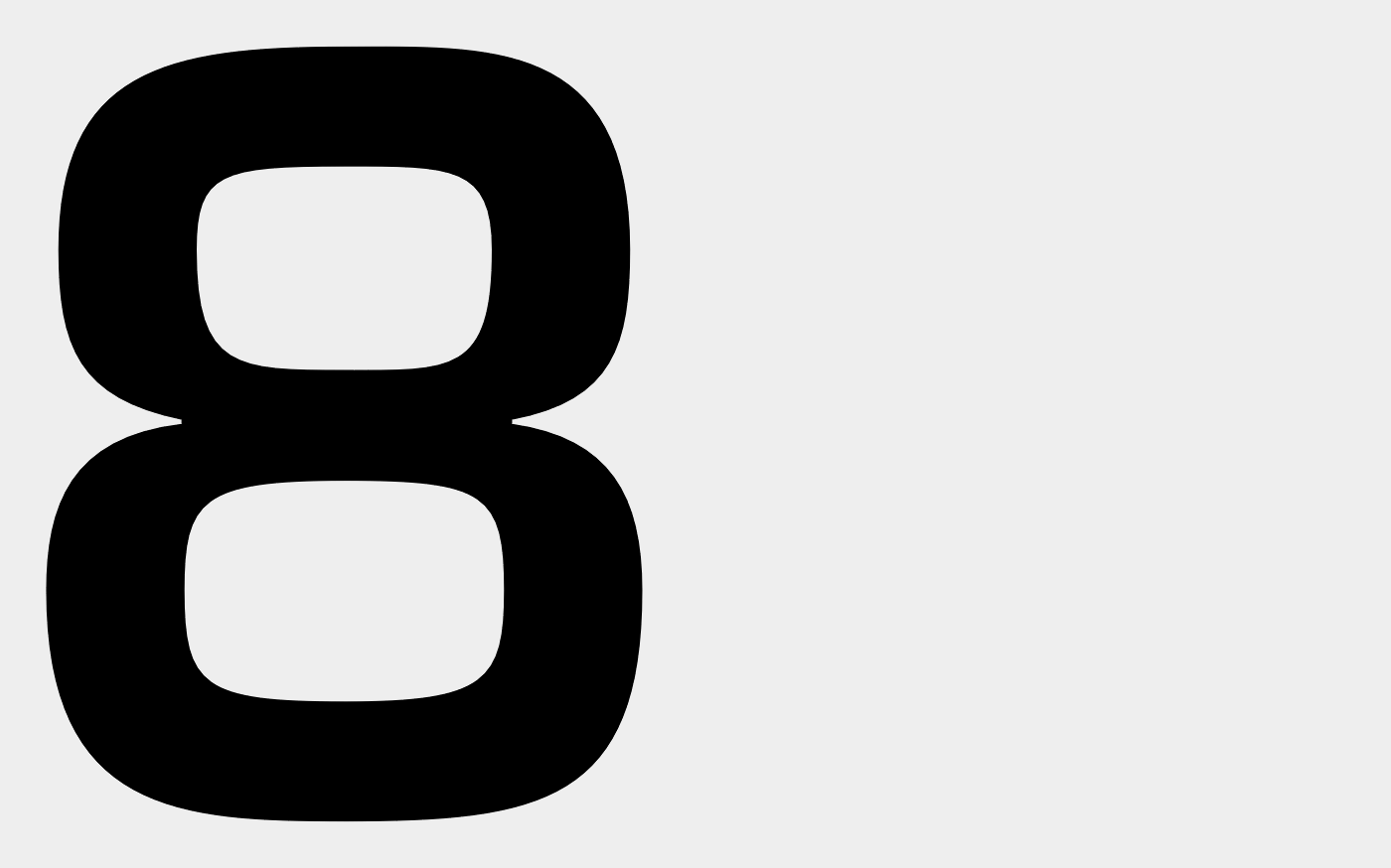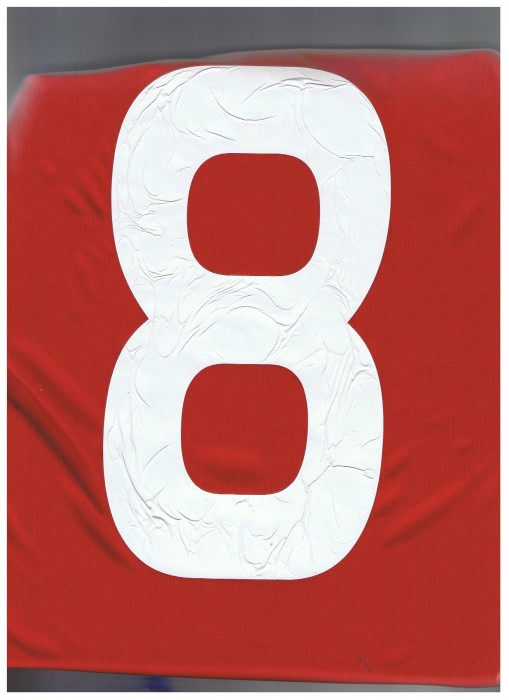
Nummer auf Fußballtrikot
ich muss mein Fußballtrikot neu beflocken lassen, da es durch die Wäsche total zerknittert aussieht. Natürlich soll es wie vorher aussehen und somit auch mit den anderen Trikots der Mannschaft übereinstimmen. Ich war schon im Fachgeschäft, um es erneuern zu lassen. Die sagten mir, grundsätzlich sei es möglich, aber dafür müssten sie erst wissen, um welche Schriftart es sich handelt. Habt ihr vielleicht eine Idee?
Ich würds eher über eine mit mehreren Lagen Stoff belegte Holzplatte spannen (auf Links) und Bügeln.
Den Flocl-Schmelzklebert bekonnt man aus dem Trikot nicht wieder heraus, daher wird das mit dem Neubeflocken, dass es wie neu aussiht eh nix, Da müsste dann ohnehin ein komplettes Ersatz-Shirt beschafft werden.
Dann die Frage: Steckt da ein größerwer Verein dahinter? Und welcher Sportkleidung-Herstellert ist das? Die liefern nämlich oft selbst die fertig geschnittenen Flock-Ziffern und Buchstaben, und geben den Font wegen Markenfälschungen gar nicht aus dem Haus. Schließlich sind die Verkäufe von Fan-Trikots ja eine nicht unerhebliche Einnahmequelle, und die Vereine wollen ja nicht, das sich die Fans unbedruckte Blanko-Shirts besorgen, und die selbst beschriften.
Mit Bügeln hab ich es schon versucht, hat leider nicht viel gebracht :-? . Die im Fachgeschäft meinten, man würde keine Kleberreste sehen, da man ja die neue 8 wieder genau darüber klebt.
Bei dem Trikot handelt es sich um eines von meinem relativ kleinen Heimatverein. Die Trikots sind von Adidas und von der Telekom gesponsert.
gestauchte Eurostile?
evtl. mal paar andere zahlen zeigen?
Andere Zahlen hab ich leider nicht, hab nur das eine Trikot zu Hause...da müsste ich mal ein bisschen in der Mannschaft rumfragen, ob sie ihre Nummer einmal abfotografieren können.
Bis dahin hab ich nur noch den Vereinsnamen, der mir ganz stark nach Impact aussieht, wobei leider die 8 überhaupt nicht dazu passt.
Die Schrift wurde auf den Trikots von Chelsea London in der Saison 07/08 verwendet. Frank Lampard trug damals die 8.
Die 13 ist hier auch noch abgebildet.
Vielleicht hilft das bei der Recherche.
Habe ich das richtig verstanden, daß die die neue 8 über die alte pressen wollen? Klebereste siehst Du da nicht, aber die Falten schlagen doch durch die neue Folie wieder durch. Abgesehen davon, daß Du dann ein ziemlich steifes Foliebrett auf Brust oder Rücken hängen hast.
Ich denke eher über die Klebereste – nicht über die ganze Acht …
Dann müßte man ja die alte 8 herunterbekommen, ohne das Textil zu beschädigen. Kann ich mir nur schwer vorstellen.
Doch, das ist gut möglich. Man kann die 8 ja jetzt so schon fast abziehen. Und dann gibt es zusätzlich noch ein Lösungsmittel...also das sollte nicht das Problem sein